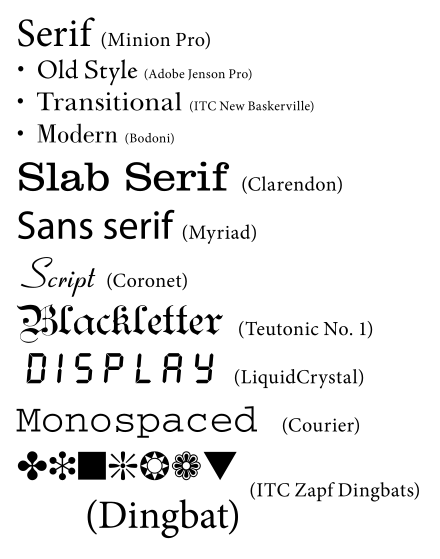
Виды шрифтов и их классификация. Использование разных видов шрифтов
В начале этой статьи можно было бы написать некую банальность, вроде «Шрифты являются неотъемлемой частью дизайна…» и прочие вводные слова. Но мы отринем такую концепцию, как устаревшую форму бытия.
Идея написания этой статьи (или даже конспекта) пришло после разговора о шрифтах — внезапно я осознал, что ничего, кроме каких-то технических знаний по этому вопросу особо не имею, и сие чувство долго не давало мне покоя, ибо знание — сила, не знание — слабость. Так и родилась идея создания конспекта по шрифтам и всему, что с ними связано. И начнём мы с исторического экскурса в историю шрифтов.
На мой взгляд, первыми шрифтами правильно будет назвать рисунки древних людей охрой на камнях. Поясню почему. Собственно, что есть сам шрифт — это графическое начертание букв и символов, составляющих единую стилистическую и композиционную систему. В зависимости от сложности языка — а мы примем за аксиому, что у древних людей язык был очень простым — шрифт соответственно будет проще.
Итак, у древних людей был примитивный язык, вероятно, не очень много слов, которые успешно заменялись картинками, которые, составляя друг с другом композицию, образовывали предложения или послания, понятные тогдашнему человеку.
Древний мир и Европа
Время шло, язык усложнялся, и взамен картинкам пришли графические обозначения букв. Сначала до этого догадались в Древнем Египте, где изобрели знаки символы, которые хотя и передавали некоторое значение/смысл/явление, в полной мере не были буквами в сегодняшнем понимании. Однако, у них уже был свой собственный выработанный стиль, рисовка и тому подобное. Первый же алфавит придумали финикийцы около 11 века до н. э., который стал первоисточником для греческого, латинского, кириллического — вот в нашем рассказе появляется алфавит, а следовательно, и шрифты в нашем современном понимании.
Греки творчески доработали финикийский алфавит. Получилось неплохо, просто и минималистично — он построен с помощью простых линий, образующих геометрические формы: квадрат, круг, треугольник. Впоследствии (но это не точно) греческий стал прообразом латинского письма, которое уже распространилось очень широко.
Самая древняя версия латинского шрифта называлась «капитальным письмом» , и имело уже целых два варианта начертания — квадратное (красивое, монументальное) и рустичное (в народе — «деревенское»). В первом варианте все буквы вписывались в квадрат, во втором же случае — простота написания с элементами декора. Да, и буквы имели ромбовидную форму.
В дальнейшем, ради ускорения написания, появился курсивный вариант написания (что с латыни переводится как «наклонный»). Скорость написания не совсем пошли на пользу — красота букв потерялась, а удобочитаемость снизилась.
В дальнейшем, для переписки сформировался унциал — спокойное величественное письмо с характерными округлыми формами.
В конце 11 — начале 12 века стал складываться новый по форме букв шрифт с острыми штрихами под названием готический. Он существовал в эпоху господства готики в архитектуре и искусстве. Готический шрифт получил широкое распространение по всей Европе, и в целом существует до сих пор. Немецкий изобретатель Иоганн Гутенберг, который изобрёл книгопечатание, в своих книгах использовал именно готический шрифт.
В эпоху Возрождения (в 14-15 веке) учёные умы Италии и Франции явили свету нечто, совсем не похожее на готический шрифт — Ренессанс-антиква . Этому шрифту художники и учёные Возрождения пытались придать логическую обоснованность, играя с формами и пропорциями букв. Например, ученик Леонардо да Винчи, Лука Пачоли в 1509 году опубликовал первые правила построения латинского шрифта — буквы предлагалось строить буквы на основе квадрата, используя для этого его диагонали и вписанную в него окружность.
Правда, получалось однообразно и не хватало драйва. Более интересный вариант начертания предложил немецкий художник и геометр Альбрехт Дюрер — он не стал изобретать велосипед и также вписывал буквы в квадрат, но стороны основного квадрата он разделил на 10 равных частей, и строил сетку, состоящую из квадратов. За толщину основного штриха брал размер шириной одной клетки, толщину соединительных штрихов тоньше основных на одну треть.
Переход в эпоху классицизма также породил новый вид шрифта, который называется Классическая Антиква . Над его созданием работали многие художники, но отдельно можно выделить Джамбатиста Бодони, Фирмена Дидо и Вальбаума (имя потерялось на просторах немецких земель). Шрифт отличает большая контрастность (примерно 1/10), наплывы округленных элементов, тонкие засечки. Шрифты, которые появились на основе антиквы, достаточно широко применяются в оформительских работах.
На рубеже 19-20 веков появляется целый ряд видов шрифтов — египетский, гротеск или рубленый, антиква-гротеск, ленточная антиква.
Египетский шрифт отличался одинаковой толщиной всех линий и засечек. Гротеск (или ещё «рубленый») имеет одинаковой толщины линии литер, но без засечек. На его основе было разработано целое семейство гротескных шрифтов.
Веб-шрифты
Термин веб-шрифт относится не к определенному формату шрифта, а к шрифтам, которые широко намекали на оптимальную читаемость при отображении на экранах компьютеров и других электронных устройствах. Некоторые из них были разработаны с нуля для электронного дисплея, в то время как другие были адаптированы задним числом. Популярные веб-стандарты позволяют разработчикам указывать использование определенных шрифтов при отображении своих страниц, даже если эти шрифты не встроены в файл или обязательно доступны на устройстве, отображающем его. В этом смысле веб-шрифты также понимаются как те, которые существуют на веб-серверах для использования в режиме реального времени для отображения онлайн-документов, которые требуют их. Некоторые из них доступны бесплатно, но другие доступны только по лицензии, с оплатой за их использование; они, по сути, арендуются.